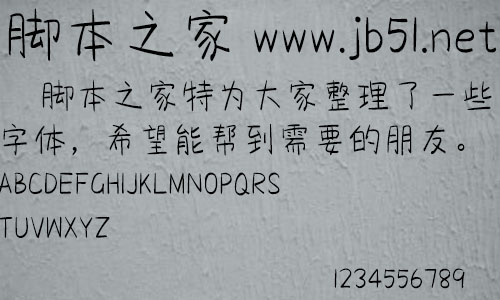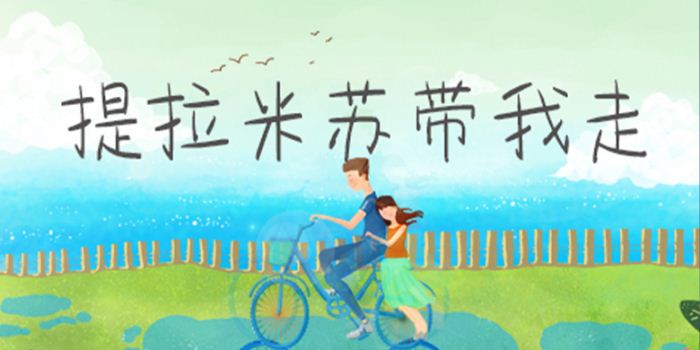
方正手跡-提拉米蘇帶我走由方正字庫 劉曄設(shè)計(jì)師出品的藝術(shù)字體,該字結(jié)字中正平和,清秀脫俗,婷婷玉立,有良好的閱讀體驗(yàn),適合應(yīng)用于藝術(shù)設(shè)計(jì)、平面宣傳設(shè)計(jì)、網(wǎng)頁設(shè)計(jì),書法等領(lǐng)域。
這款字行筆簡練流暢,結(jié)字中正平和,清秀脫俗,婷婷玉立,有良好的閱讀體驗(yàn)。適用于少年兒童類的書刊、品牌廣告和產(chǎn)品包裝設(shè)計(jì),以及社交網(wǎng)絡(luò)的個性化用字。